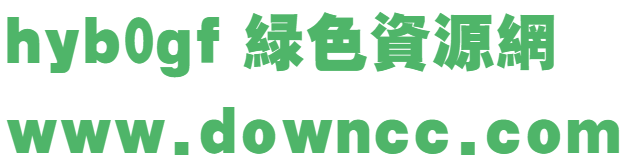
hyb0gf
hyb0gf字體又名漢儀超粗黑繁,是一款壯重醒目的漢儀黑體字體,結(jié)構(gòu)端正,號召力較強(qiáng),應(yīng)用效果良好,需要繁體字體的朋友快來綠色資源網(wǎng)下載吧!
hyb0gf字體特點(diǎn)
漢儀超粗黑簡保持著黑體字的共有特點(diǎn),筆畫粗壯有力,橫豎筆畫粗細(xì)比較接近,兩端平直,加鋒較小,筆畫簡潔粗壯!